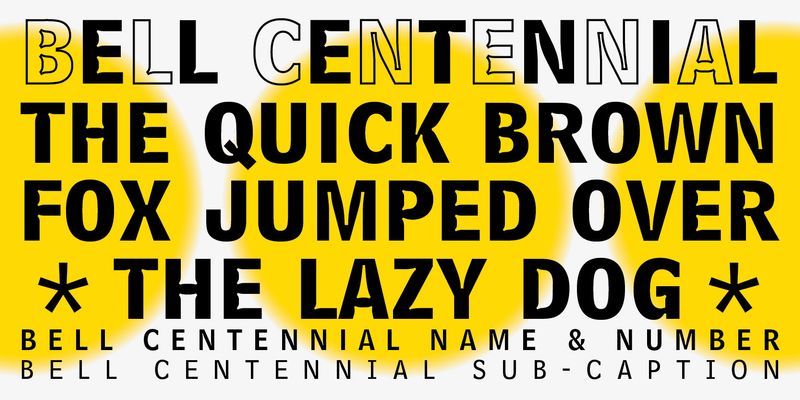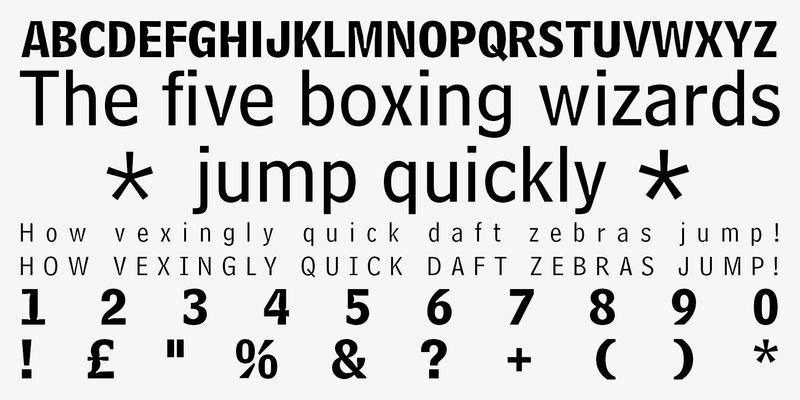
Matthew Carter desenvolveu a Bell Centennial em 1978, especificamente para a AT&T Corporation (o nome homenageia seu centésimo aniversário) para uso em listas telefônicos. Carter a desenvolveu visando a alta legibilidade em tamanhos pequenos e a composição em alta velocidade em máquinas de composição com tubo de raios catódicos. A Bell Gothic, fonte originalmente feita para listas telefônicas em 1937 e para composição nos linotipos de composição a quente, não podia mais ser usada nessa nova tecnologia. A Bell Centennial é um design condensado sem serifa que garante grande economia de espaço sem prejudicar a alta legibilidade. Ela pode ser usada para fins de exibição modernos e, é claro, para letras miúdas e listas. Sua versão alternativa, Bell Centennial Bold Listing, é escrita sobre uma linha de base padrão, enquanto a versão original é situada muito abaixo da linha de base e não fica bem com outras fontes na mesma linha.